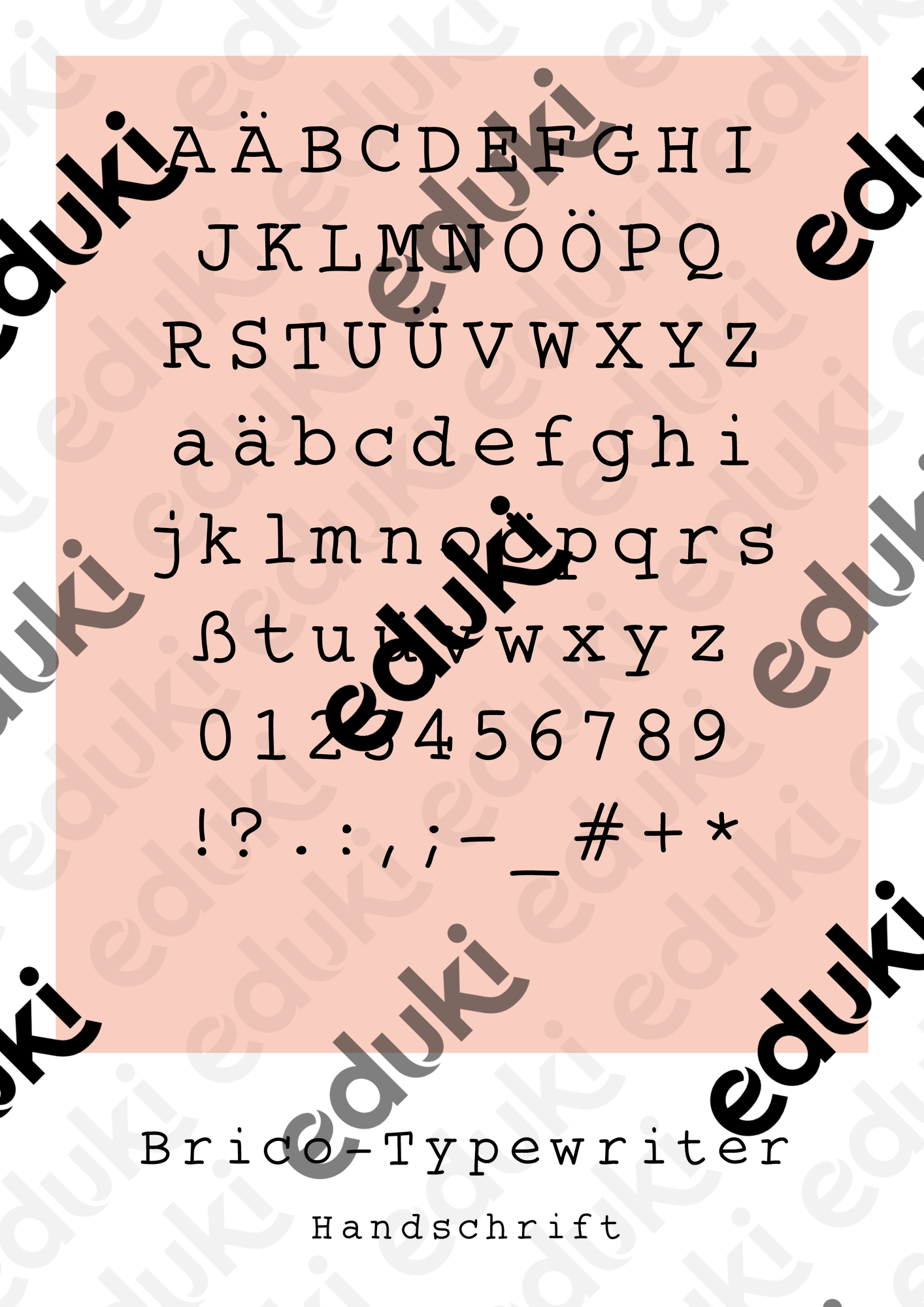
selbst erstellte Schriftarten - Schriftart für dein Arbeitsmaterial - BricoTypewriter - Bricoliene - Deckblatt
Selbsterstellte Schreibmaschinenschrift, die sich wunderbar zur Erstellung von Arbeitsblättern oder anderem Unterrichtsmaterial eignet.
Schriftart für dein Arbeitsmaterial - BricoTypewriter